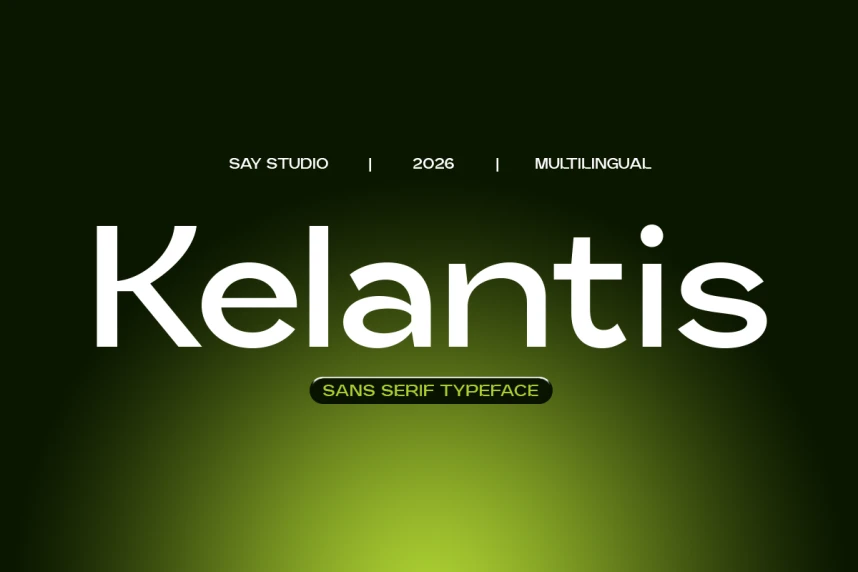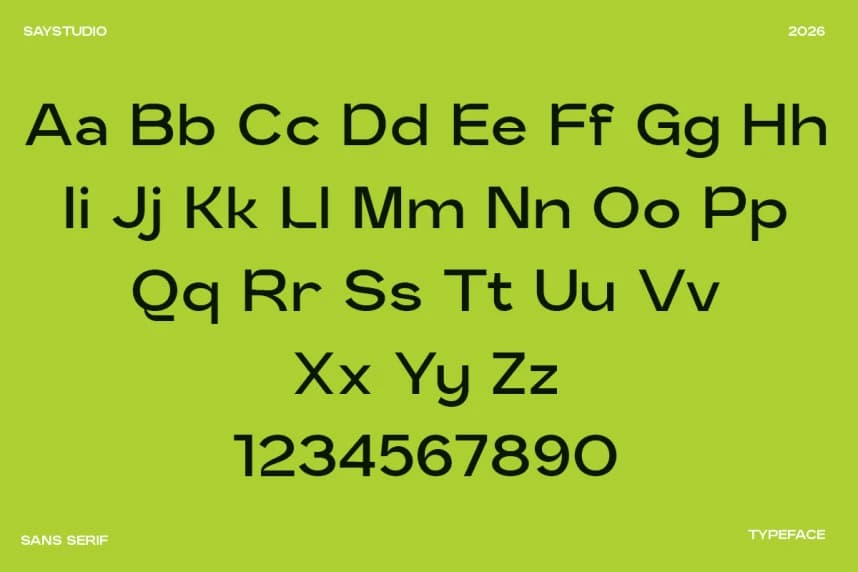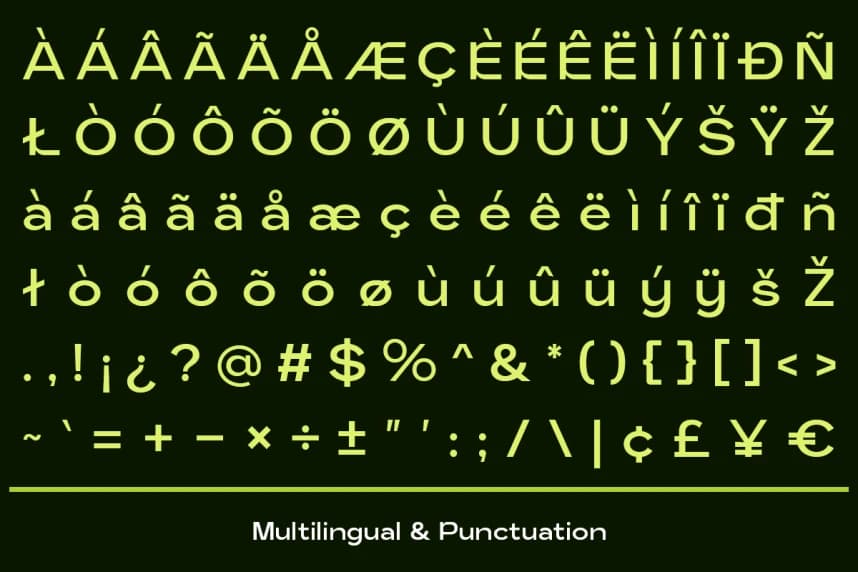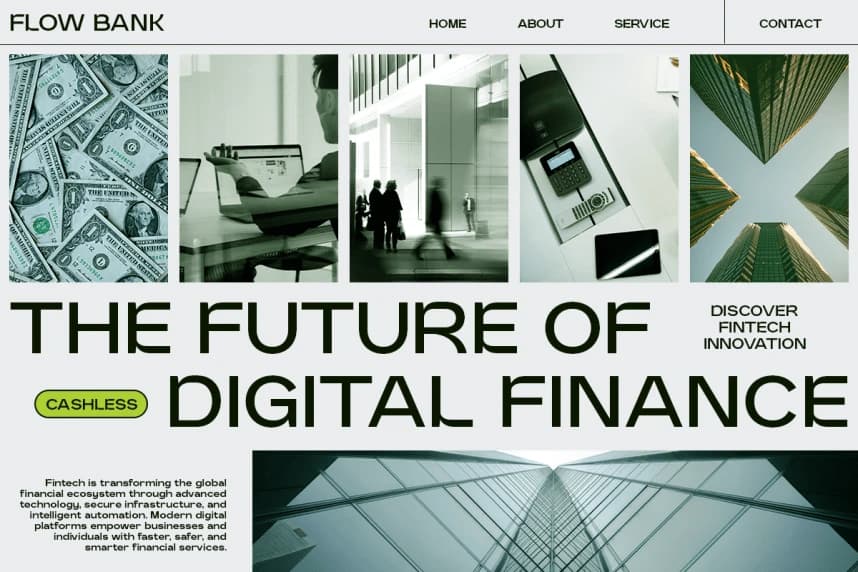
Kelantis DEMO Font
Kelantis DEMO Font, netlik, sadelik ve çağdaş görsel etki için tasarlanmış modern bir sans serif yazı tipidir. Temiz çizgiler ve dengeli oranlarla tasarlanan bu yazı tipi, bugün dijital ve marka dünyasına mükemmel uyum sağlayan şık ve profesyonel bir görünüm sunar. Minimal yapısı.
Kelantis DEMO Font, netlik, sadelik ve çağdaş görsel etki için tasarlanmış modern bir sans-serif tipografidir. Temiz hatlar ve dengeli oranlar ile tasarlanmıştır; bu font, şık ve profesyonel bir görünüm sunar ve günümüz dijital ve marka iletişimi ortamına mükemmel bir şekilde uyum sağlar. Minimal yapısı, hem büyük başlıklar hem de daha küçük metin uygulamaları arasında mükemmel okunabilirlik sağlar.